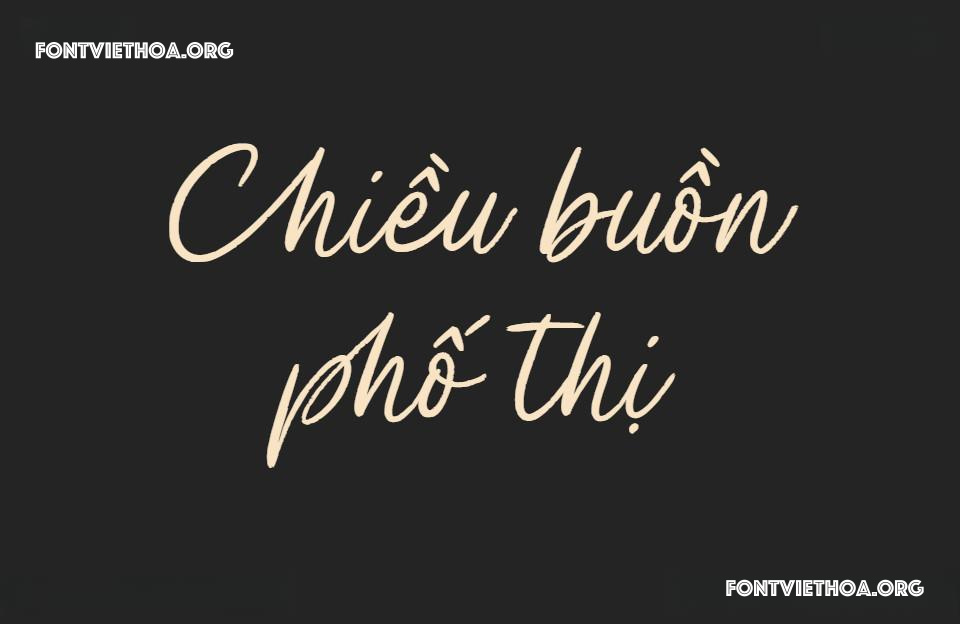
Tên font: Font Việt hoá VIP Billie James – Brush
Tác giả: Damarletter
Font Việt hoá VIP Billie James là một font chữ dạng viết tay, nó cũng là kiểu font brush. Font có thể dùng cho các thiết kế thiệp hoặc spa mỹ phẩm làm đẹp. Với kiểu dáng đẹp và hiện đại, font này sẽ mang lại cho bạn một sự lựa chọn tuyệt vời cho các dự án thiết kế của mình.
Font Việt hoá VIP Billie James được thiết kế để mang lại sự mềm mại và tinh tế cho các thiết kế của bạn. Với các đường nét cong mềm mại và các chi tiết tinh tế, font này sẽ giúp bạn tạo ra các thiết kế đẹp và chuyên nghiệp.